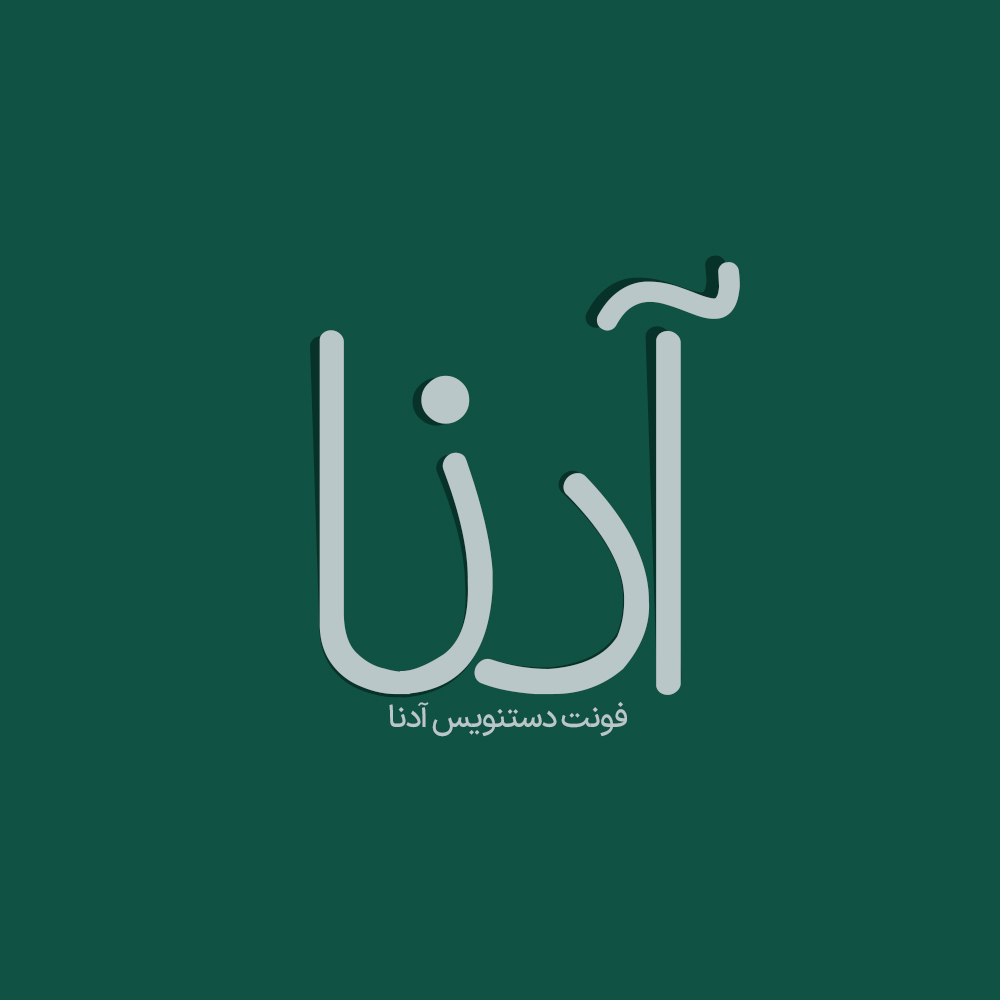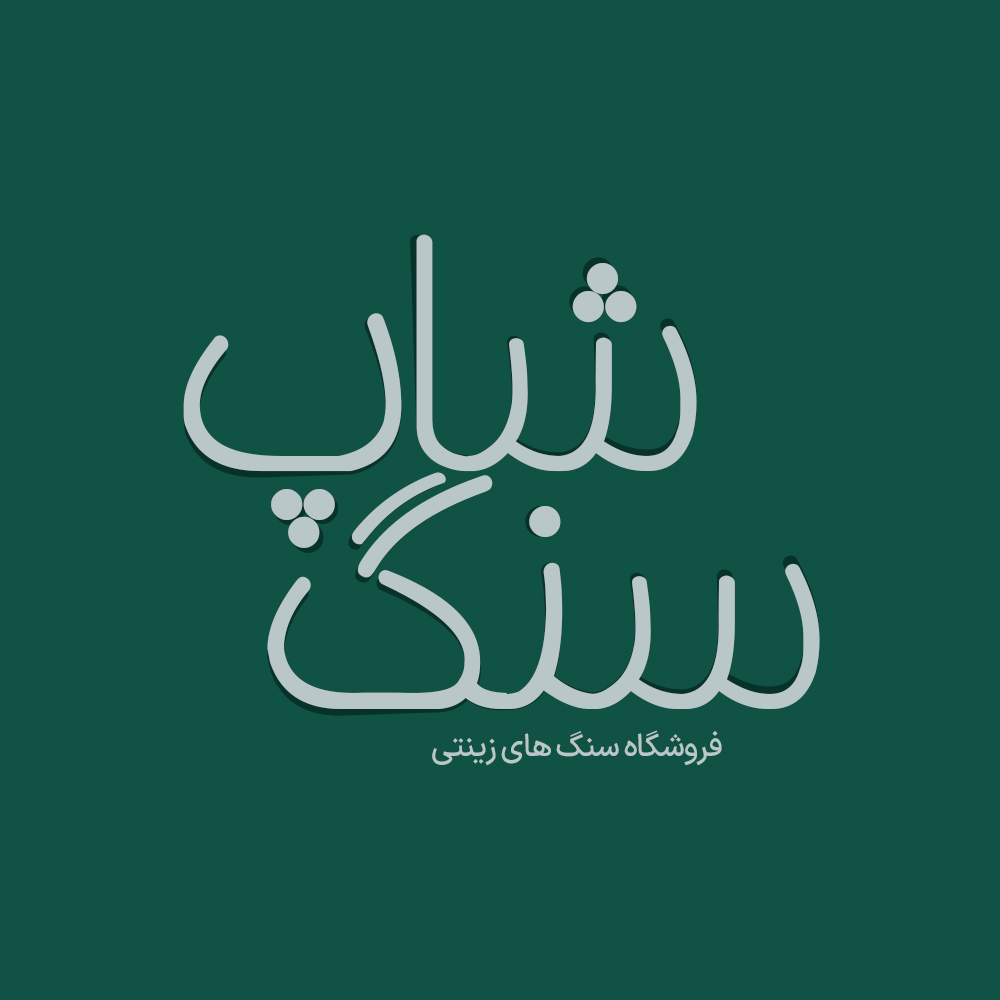
فونت فارسی آدنا Adena Font
فونت دستنویس آدنا از سری فونتهای فارسی حرفه ای می باشد که مناسب برای استفاده در قسمت های خاص از تبلیغات، طراحی عکس نوشته ها و ایجاد فضای گرم و صمیمی در گرافیک کاربرد دارد.
فونت دستنویس آدنا یک فونت متفاوت برای طراحی انواع امور گرافیکی به خصوص طراحی انواع لوگوتایپ و تایپوگرافی می باشد اما پیشنهاد میکنیم برای تایپوگرافی بهتر در نرم افزار های گرافیکی (فتوشاپ،ایلاستریتور،کورل و…) استفاده کنید تا با کمی چینش و سفارشی سازی یک خروجی حرفه ای داشته باشید. در ادامه برای شما نمونه تایپ های این محصول حرفه ای رو آماده کردیم که میتونید مشاهده کنید.
پیشنمایش و نمونه تایپ های فونت آدنا